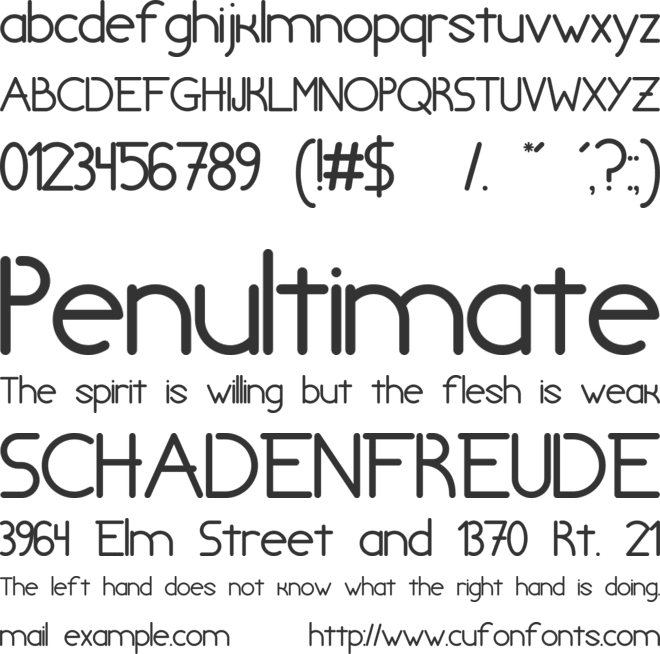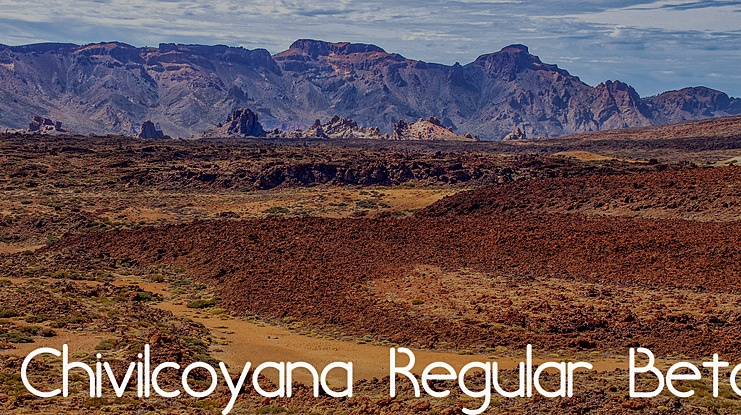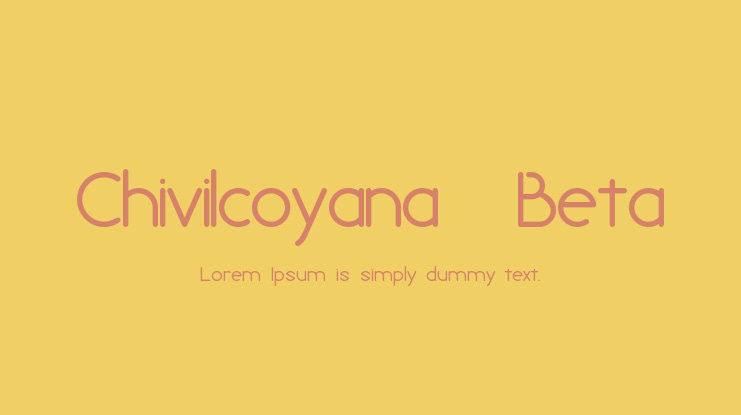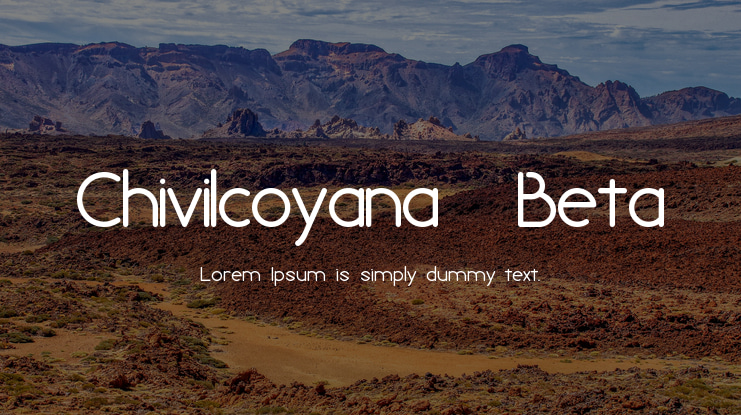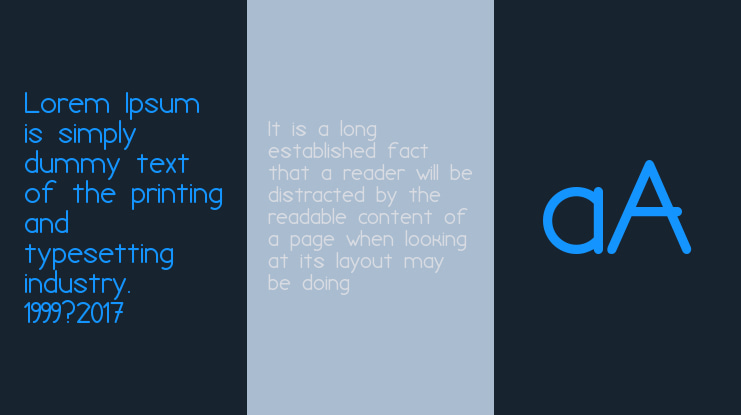
Chivilcoyana Beta Font
Juan Ignacio Felice
Chivilcoyana Regular es una versión Beta. La tipografía tiene un ancho fijo en sus trazos. Contiene mayúsculas, minúsculas, signos de puntuación, números y acentos. Faltan ligaduras y ajustes de kerning y tracking.